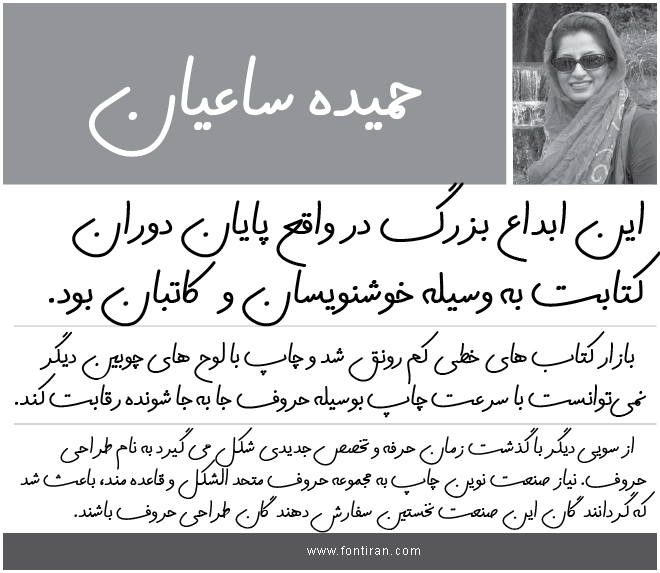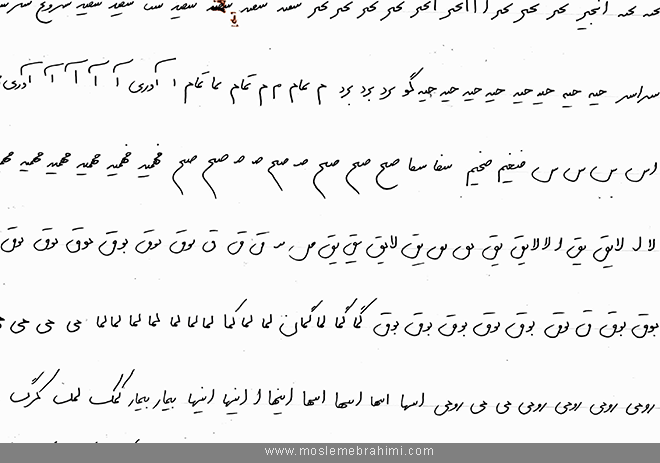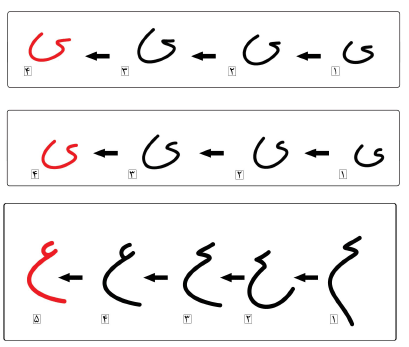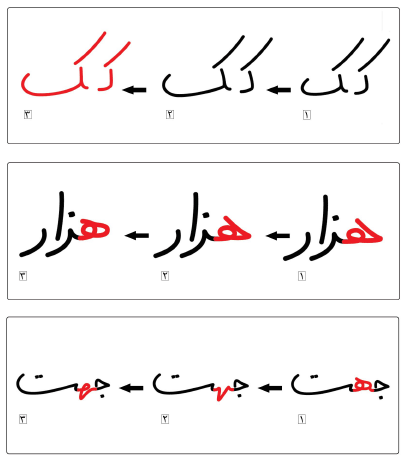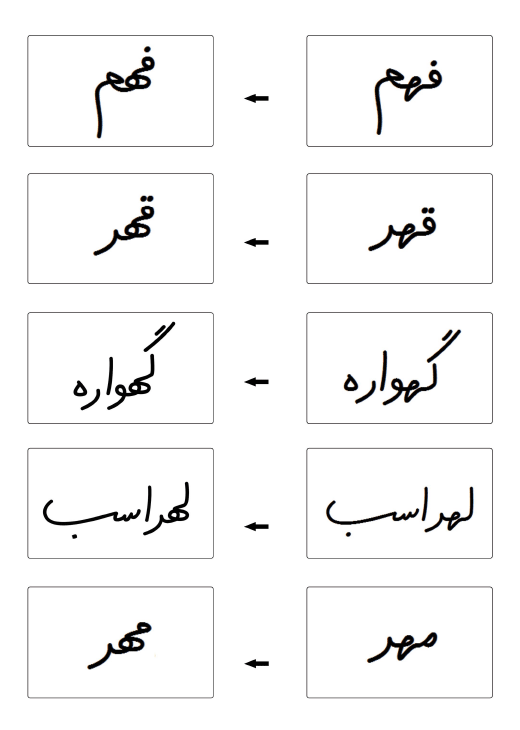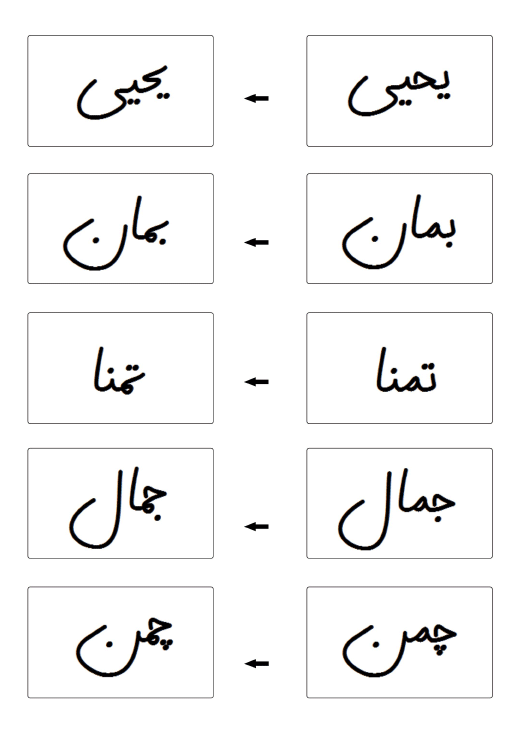
تایپ فیس دست نویس حمیده ساعیان در مقایسه با سایر فونت ها از تنوع اشکال، آزادی و راحتی بیشتری برخوردار است و در نتیجه به یک دست خط خودکاری واقعی نزدیک تر می باشد.
فونت حمید ساعیان
تایپ فیس دست نویس برای درج نکته های خاص در تبلیغات، ایجاد فضاهای شاعرانه و صمیمی در گرافیک محصولات فرهنگی کاربرد زیادی دارد.